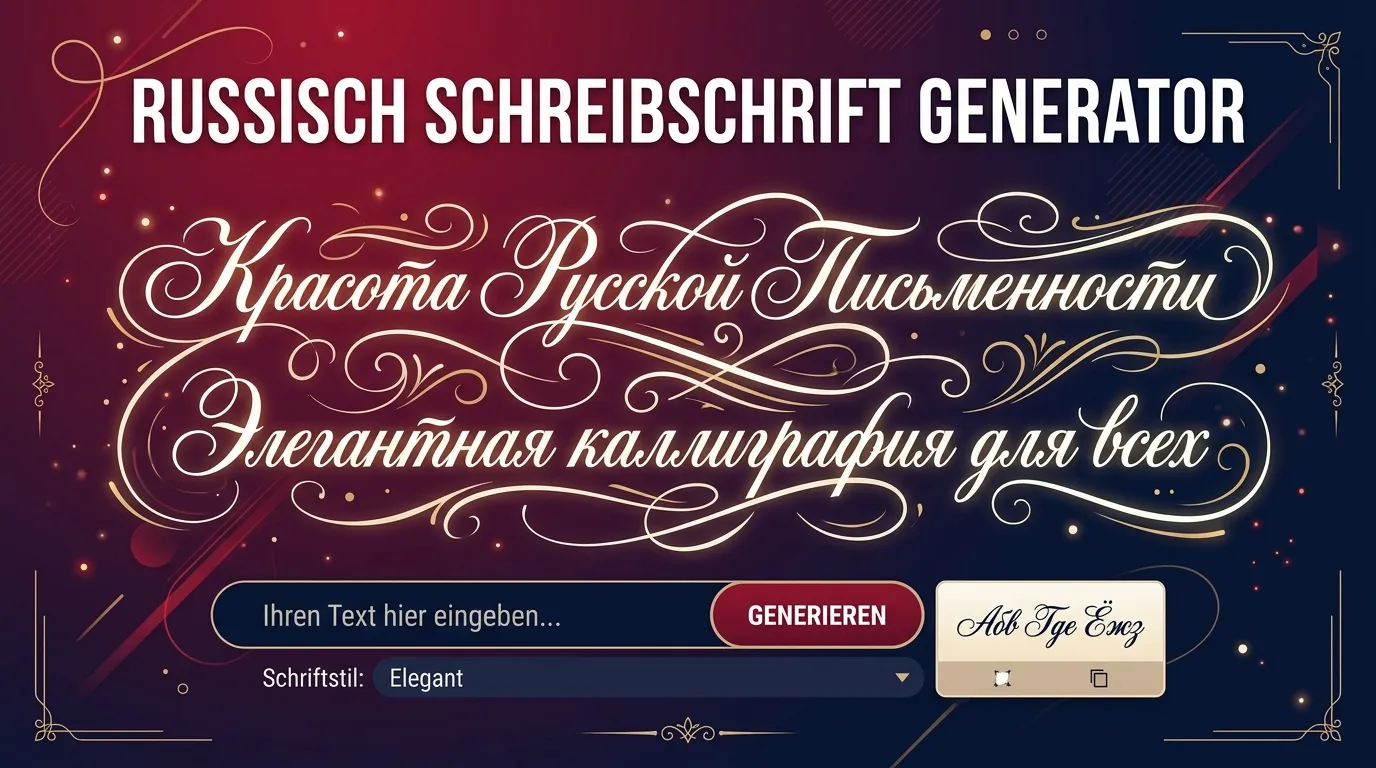
Russisch Schreibschrift Generator
Hinweis: Umlaute (ä, ö, ü, ß)
Deutsche Umlaute und ß haben keine Russisch Schreibschrift-Entsprechung im Unicode-Standard und erscheinen daher in normaler Schrift neben den umgewandelten Buchstaben. Das ist eine unvermeidliche technische Einschränkung aller Russisch Schreibschrift-Generatoren, nicht ein Fehler unseres Tools.
Russische Schreibschrift: Warum sie so anders aussieht
Russische Schreibschrift unterscheidet sich fundamental von ihrer Druckform: weit stärker als die Unterschiede zwischen Druck- und Schreibschrift im Deutschen. Viele kyrillische Buchstaben sehen in Schreibschrift völlig anders aus: Das gedruckte „Д" (D) wird in Schreibschrift zu einer Schlaufe, die an ein lateinisches „g" erinnert. Das gedruckte „Т" (T) wird zu etwas, das wie ein lateinisches „m" aussieht.
Diese Unterschiede machen russische Handschrift für Nicht-Muttersprachler zu einer echten Herausforderung. Selbst russische Erstklässler verbringen 2-3 Jahre damit, Schreibschrift (пропись) zu erlernen: mit speziellen Übungsheften voller Schleifen- und Verbindungsübungen.
Neben kyrillischen Stilen bietet unser Generator auch lateinische Schreibschrift-Stile : von Sütterlin bis elegante Kursive.
Einsatzgebiete: Social Media, Gaming und Sprachlernen
Kyrillisch-inspirierte Schriftstile sind besonders beliebt auf Discord, in Gaming-Communities und auf Social Media. Sie verleihen Spielernamen einen internationalen, mysteriösen Charakter: besonders in russisch geprägten Gaming-Communities (CS:GO, Dota 2, World of Tanks).
Für Deutschsprachige mit russischen Wurzeln oder Russisch-Lernende bietet der Generator eine schnelle Möglichkeit, Namen und kurze Texte in kyrillisch-inspirierten Stilen zu visualisieren: als Ergänzung zum Sprachunterricht oder für persönliche Projekte.